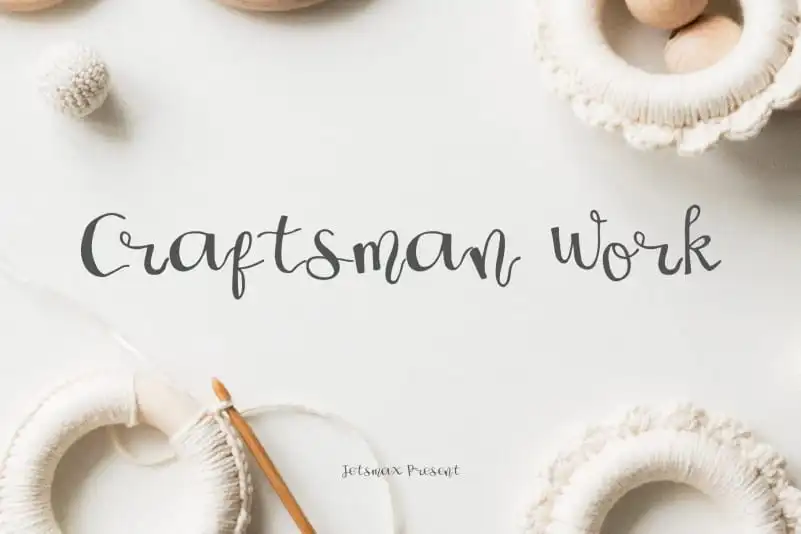
Craftsman Work Script Font – Fonte Grátis
Craftsman Work Script Font
A fonte ‘Craftsman Work Script Font’ é uma escolha perfeita para quem busca um estilo elegante e autêntico que lembra a mão escrita real. Desenvolvida pelo designer jetsmax, essa fonte escrita à mão oferece um design cuidadoso e delicado, projetada para imitar a aparência de uma escrita manual perfeita. Ela traz aos seus projetos um toque natural e autêntico que não apenas adiciona personalidade ao texto, mas também cria um aspecto muito realista. Perfeita para aplicativos como cartazes de eventos, artigos de design gráfico ou até mesmo para o design de websites onde uma escrita à mão impecável pode dar um toque único e sofisticado. Seja em sua tipografia editorial ou quando você está criando materiais publicitários, essa fonte irá deixar seu trabalho com um encanto autêntico, tornando-se uma ótima adição à sua coleção de recursos gráficos.
Designer: jetsmax